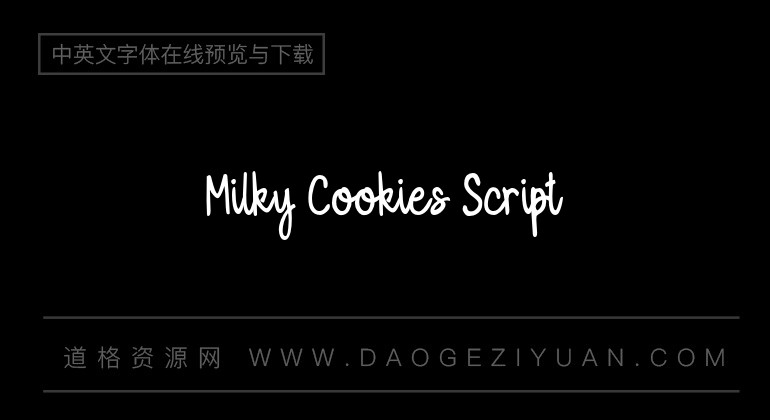
Milky Cookies Script
Milky Cookies Script 是一种手写风格的字体,具有柔软、流畅、自然的特点。该字体的设计灵感来源于传统手写书法艺术,结合了现代设计的元素,使其独具特色。字母间距适宜,字母的大小和形状都非常匀称,使得整个字体看起来非常美观。此外,该字体还具有多种风格和变体,可以满足不同场合的需求。Milky Cookies Script 字体适合用于卡片、海报、标志、广告、包装、书籍和杂志排版等多个领域。
Milky Cookies Script是一款非常不错的手写艺术字体,具有很好的视觉感,适合于文化类的宣传设计、商业类品牌的广告和产品包装设计以及个性化文字排版等较多场景。